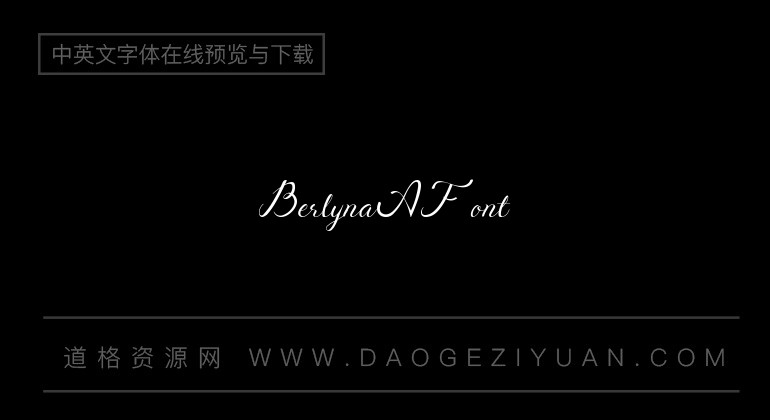
Berlyna是一种现代化的手写风格字体,具有时尚和优美的外观。该字体设计师为Mikrojihad Typography,于2018年推出了该字体。Berlyna字体是一种有机的字体,展现了手写笔触的不规则性和流畅性,同时又具有一定的清晰度和易读性。此字体适用于许多场合,如印刷品设计、品牌标志、海报、包装设计、网页设计等。Berlyna字体有多种字重可供选择,可根据具体应用选择不同的字重以达到最佳效果。内容介绍
Berlyna Font是一款非常不错的手写艺术字体,具有很好的视觉感,适合于文化类的宣传设计、商业类品牌的广告和产品包装设计以及个性化文字排版等较多场景。